Tendances des types : 2023 Tendances des types d'été au deuxième trimestre
Il est très difficile de prédire les tendances d'à peu près n'importe quoi, et cela pose de nombreux problèmes. Repérer les tendances, en revanche, est beaucoup plus facile. Surtout si vous disposez d'une base de données. Et nous avons une base de données.
C'est exactement ce que nous avons fait pour cette mise à jour de Type Trends. Mais nous ne nous sommes pas contentés d'examiner les différentes polices. Nous avons utilisé les Hot New Polices comme base de données pour repérer les tendances.
En plus d'un grand nombre de nouvelles polices, nous avons trouvé quatre tendances définitives dans la conception des polices de caractères. Nous les appelons :
- Changeurs de poids
- Pas un Sans comme les autres
- Une fantaisie accessible
- Amusement et jeux
Changeurs de poids
Les Weight Shifters bouleversent les normes traditionnelles en matière d'accentuation des caractères. Dans les formes de lettres traditionnelles, l'accent est dérivé d'un aspect connexe de l'écriture ou du lettrage créé à l'aide d'un instrument d'écriture à large bord (pensez à un pinceau large ou à un stylo plat). (C'est subtil, mais on peut même le voir dans certains caractères sans empattement.
L'accentuation traditionnelle des caractères est née dans un monde analogique. Mais nous vivons depuis longtemps dans un monde numérique, et les créateurs de caractères s'adaptent à cette réalité. Le changement de poids polices attire clairement l'attention, ce qui en fait d'excellentes conceptions d'affichage. Ils peuvent également créer une ambiance moderne et parfois élégante.
Gyst
Les polices de caractères traditionnelles de style ancien ont le poids de trait le plus important à environ 2:00 et 8:00. Gyst fait pivoter cette contrainte à 1:00 et 7:00, faisant des caractères ronds presque un italique inversé. Le résultat est un design qui fusionne astucieusement les principes des caractères sans empattement et des caractères anciens. Gyst est à la fois élégant et avant-gardiste.
Remixa
Les traits de Remixa limitent son utilisation aux grands formats, mais il apporte clairement l'essence de la modernité et de l'élégance intemporelle à presque tous les projets. Même les poids les plus audacieux sont légers.
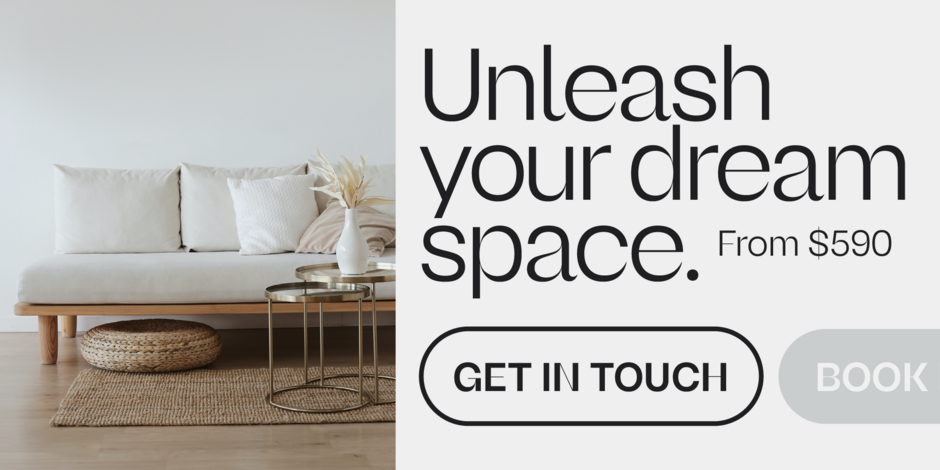
ZT Vollun
On peut dire que Vollun ne ressemble à aucun autre caractère sans empattement. Ses traits capillaires apparaissent dans les endroits les plus improbables. Et pourtant, cela fonctionne. C'est une police de caractères qui a de l'esprit et qui a le courage de dire : "Je ne suis peut-être pas comme les autres sans, mais je peux faire le travail avec confiance - et une touche de cool."
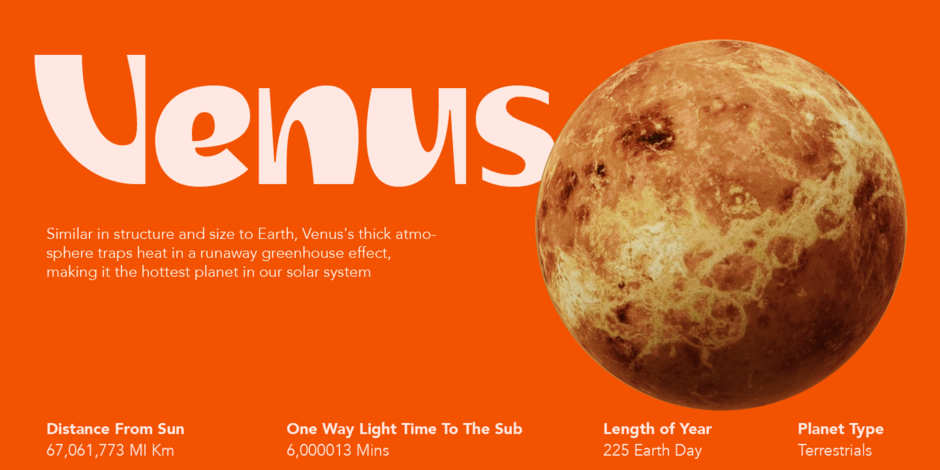
Pas un Sans comme les autres
Qu'ils soient géométriques, grotesques ou humanistes, nous attendons certaines choses des caractères sans empattement. Les terminaisons délicatement incurvées, les courbes sensuelles, les ligatures imbriquées et les accents numériques renforcés ne font généralement pas partie du mélange. Mais cette tendance s'appelle "Not Your Average Sans".
Moralité
La moralité se prête naturellement à la conception de marques et de logos. Elle s'intègre et se distingue à la fois. À première vue, il s'agit d'une police de caractères géométrique bien conçue. En y regardant de plus près, on remarque toutefois des terminaisons de base légèrement incurvées et plusieurs caractères minuscules décentrés à gauche.
Twogether Sans
Sans légèrement quadrillé (pour faciliter l'espacement des lettres), Twogether Sans combine des traits opulents avec des courbes de base réduites, pour créer un design qui ne sera pas confondu avec un sans ordinaire - sans pour autant faire étalage de sa diversité.
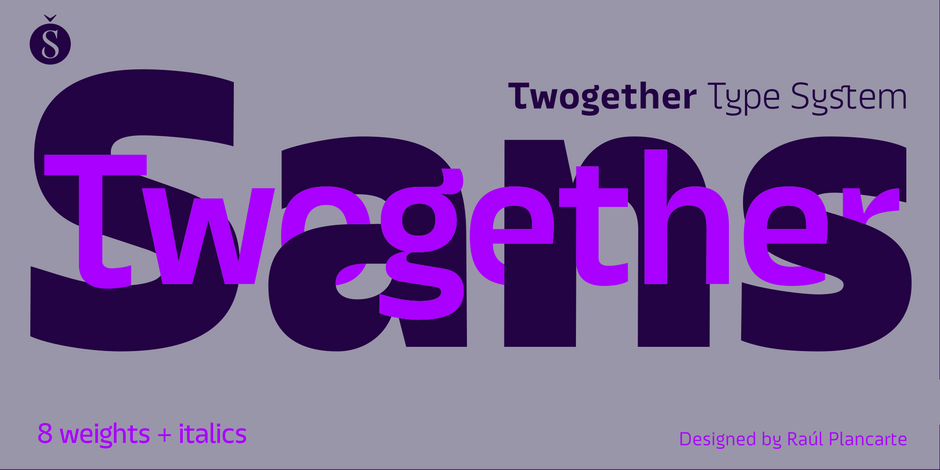
Glitch
Glitch a un héritage numérique évident, mais n'est pas dur ou exigeant. Il est clair qu'il fait une déclaration, mais il ne crie pas. S'il est idéal pour les titres, les affiches et d'autres environnements de grande taille, Glitch est aussi étonnamment facile à lire dans des blocs de texte courts.
Une fantaisie accessible
Le site polices est sympathique, accueillant et a tendance à être un peu plus dodu. Ils créent également une ambiance, encouragent la lecture et créent une atmosphère affable. Cette tendance n'est pas vraiment nouvelle. Elle remonte au début du XXe siècle. Toutefois, les caractères suivants apportent un regard neuf sur les polices de caractères qui sont affables et plus qu'attachantes.
Mangue mûre
Avec un peu d'ITC Souvenir et de Cooper Black et beaucoup de sa propre personnalité, Ripe Mango a plus d'attitude et de fantaisie que ses prédécesseurs. Des caractères tels que a, e, g, y, G, Q et T confèrent au dessin une qualité plus extravagante et insouciante. Ripe Mango est à la fois joyeux et détendu.
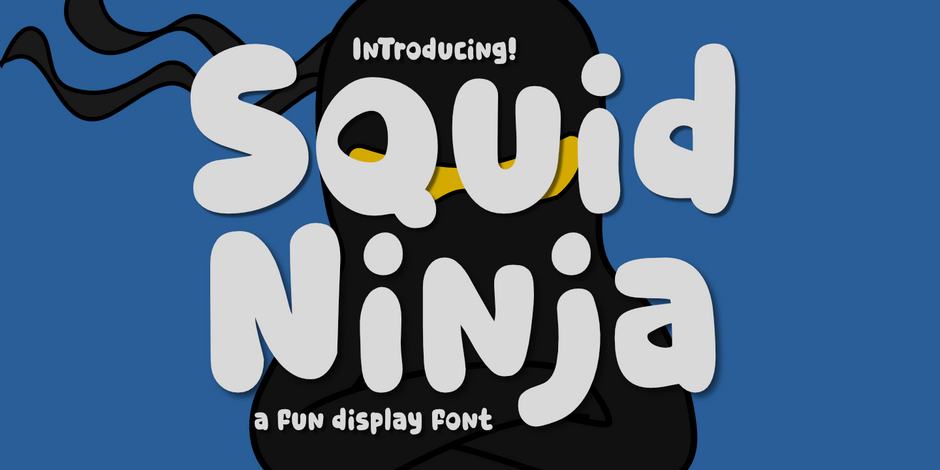
Comme toute autre activité créative, les tendances en matière de conception de polices de caractères vont et viennent - et il est rarement conseillé de les suivre. Mais si la popularité est inconstante, les tendances susmentionnées donnent un aperçu de la nature changeante de la créativité typographique et, peut-être, une plate-forme pour construire quelque chose de nouveau et de frais dans votre projet Suivante .